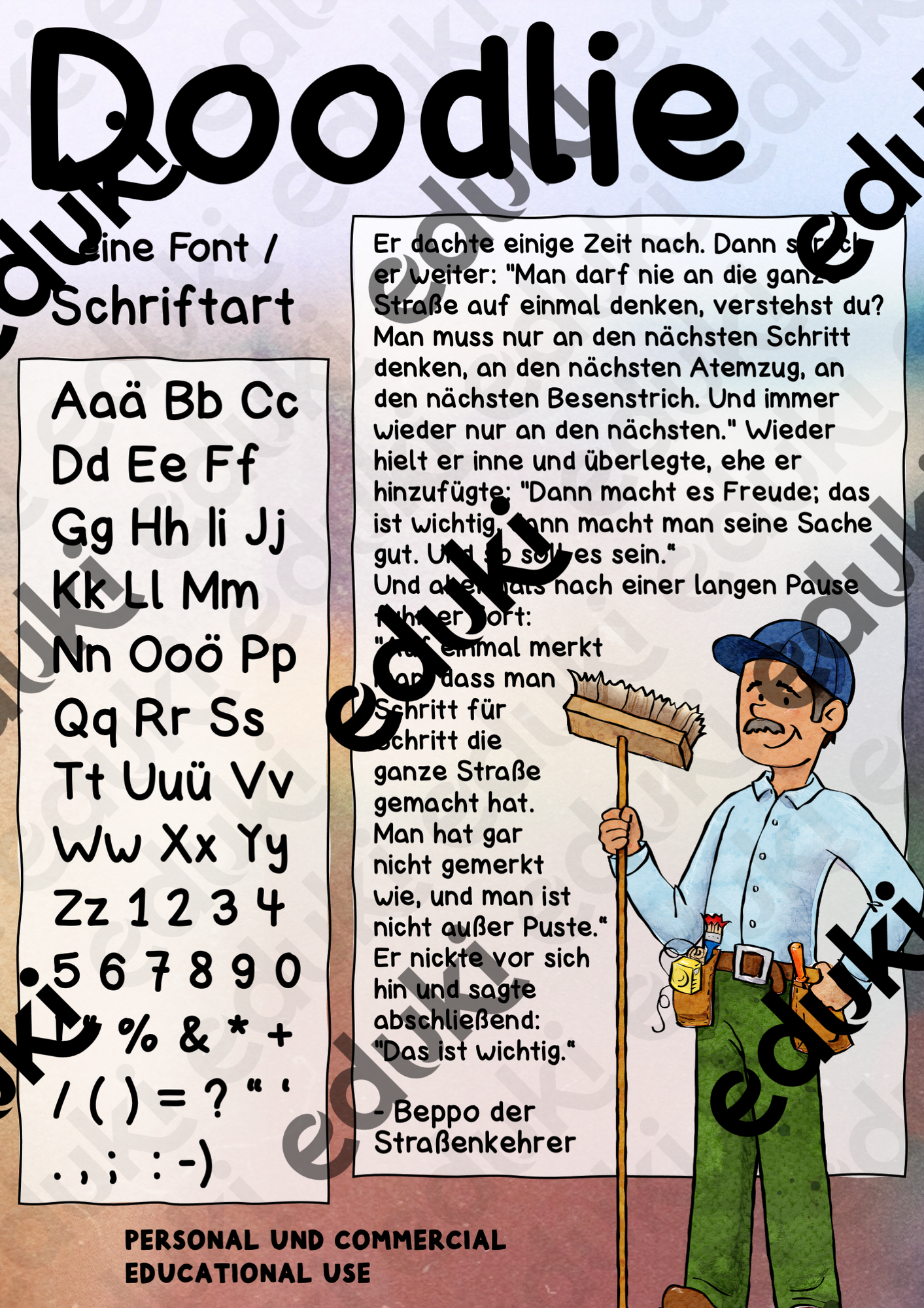
selbst erstellte Schriftarten - Doodlie - Font / Schriftart - Quirlidoodle - Deckblatt
Eine schöne und saubere handgeschriebene Schriftart.
Doodlie - Font / Schriftart